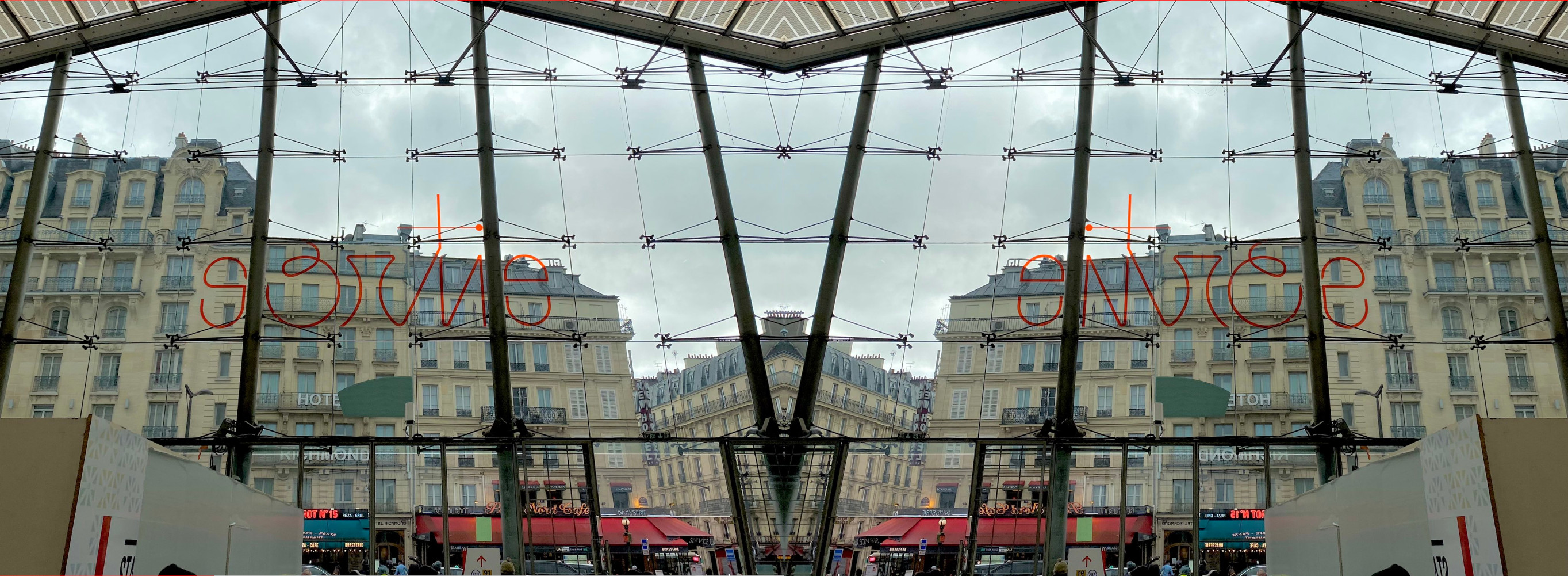
Le 3 déc. 2021 à 06:44, dominique_chassaing@xxxxxxxxxxx a écrit :Entrée / Sortie
Gare du Nord, à Paris. Une création de Patrice HamelMerci.De la pure typoésie à la Jérôme Peignot.—